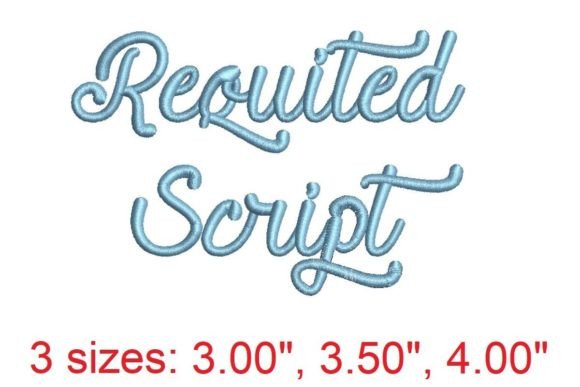
Requited Script Embroidery Font
Trouver les bons éléments de conception peut être un défi, mais Requited Script Embroidery Font propose une collection exceptionnelle qui rehausse instantanément votre travail.
Conçu avec précision, Requited Script Embroidery Font offre des vecteurs nets, une typographie fluide et une licence commerciale pour une tranquillité d'esprit.
Que vous créiez des produits POD (impression à la demande), des invitations de mariage ou des visuels pour les réseaux sociaux, Requited Script Embroidery Font est un choix idéal.